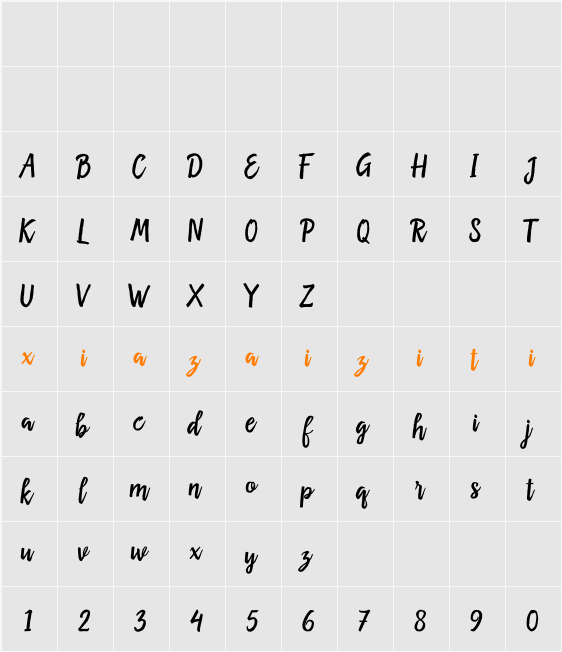
Carolinea
Carolinea,这款字体结构工整、笔画清晰,兼顾美观与易读性,适用于标题、正文、海报、包装、LOGO 等多种场景。字形优雅稳定,风格百搭耐看,适配日常排版与创意设计,让文字呈现更舒适、更具质感。Carolinea一笔一画,皆是细节,以均衡的比例、流畅的线条打造舒适视觉体验,字形端正大气,风格简约现代。无论是商业设计、品牌宣传还是日常排版,都能轻松驾驭,让文字更有格调与力量。Carolinea字体下载。